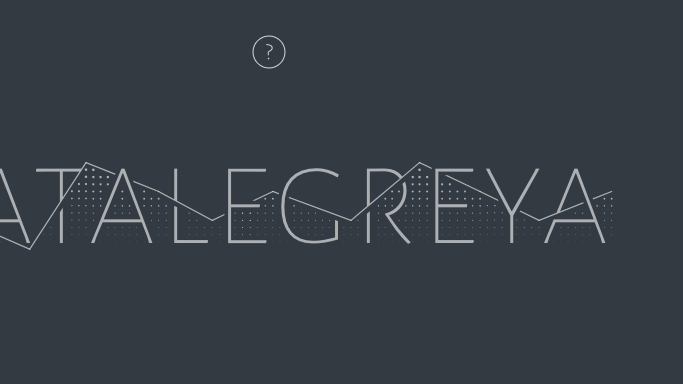
Dieser Font lässt euch mit Text versehene Datenkurven erstellen
Datalegreya macht sich die Programmiermöglichkeiten des Opentype-Standards zunutze. (Screenshot: t3n)
Wer zum Beispiel ein Reporting erstellt, in dem viele kleine Diagramme enthalten sein sollen, jedes mit nur wenigen Daten darin, kann alle diese Diagramme aus Excel kopieren und einfügen und sie anschließend so formatieren, dass sie sich ins Corporate Design einfügen – oder eben einen Font wie Datalegreya verwenden.
Reportings, Aktienkurse, Wetterberichte
Datalegreya ist wie Google Fonts Open Source und damit kostenlos. Er wurde spezifisch dafür entworfen, Datenkurven mit Text zu versehen. Als Basis für das Design der Schriftart diente Alegreya Sans Thin SC, ein Open-Source-Font aus dem Portfolio des Schriftendesigners Juan Pablo Del Perla. Der Font eignet sich besonders gut für Szenarien, in denen nur wenig Platz für Text verfügbar ist. Die zugehörige Website listet Jahresberichte, Wetterberichte und Aktienkurse als mögliche Anwendungsfälle.
Funktioniert mit allen Opentype-fähigen Systemen
Dataleygreya lässt sich mit allen Opentype-fähigen Systemen – zum Beispiel MS Word, Apples Textedit oder der Adobe-Suite – nutzen. Datalegreya ist Standards-compliant, sodass der Font sowohl im Web als auch im Zusammenspiel mit den genannten Programmen funktioniert. Jedes der Zeichen in Datalegreya hat 16 Varianten, sodass die Schrift verschiedene Werte wiedergeben kann. Die Nutzung in einer Datenkurve erfordert die Eingabe eines Sonderzeichens, gefolgt von einer Zahl hinter jedem Buchstaben. Die Schrift unterstützt die Integer-Werte 0 bis 3, zur genauen Darstellung komplexerer Datensätze eignet sie sich daher weniger. Den aus Sonderzeichen, Ziffern und Buchstaben bestehenden Code konvertiert Datalegreya dann automatisch zu einer Kurve, die den ausgewählten Werten entspricht. Natürlich lässt sich der Font auch ohne Datenkurven verwenden.
Ähnliche Ansätze
Der Ansatz hinter Datalegreya ist nicht neu. Die Technologie dahinter, Opentype-Transformationen, gibt es bereits seit 2016. Damals gab es allerdings nur einen einzigen Font, der davon Gebrauch machte: Chartwell. Chartwell ermöglicht das Erstellen von Balken- und Tortendiagrammen nach einem ähnlichen Prinzip wie Datalegreya, ist im Unterschied dazu aber weder kostenfrei noch Open Source. Andere Schriften, die in eine ähnliche Kerbe schlagen, sind AtF-Spark – Datalegreya wohl am ähnlichsten – und Amazing Infographic, eine Schrift, die wie Chartwell das Erstellen von Balken- oder Tortendiagrammen und zudem von Personendiagrammen ermöglicht.
Der Nachteil
Der offenkundige Nachteil dieser Schriften, der insbesondere bei einer Verwendung im Web bedacht werden sollte: Sie sind nicht barrierefrei. Menschen, die eine Web-Anwendung über einen Screenreader besuchen, bekommen anstelle der Datenkurven mit Text den zugrundeliegenden „Code“, also Klammern, Ziffern und Sonderzeichen vorgelesen.